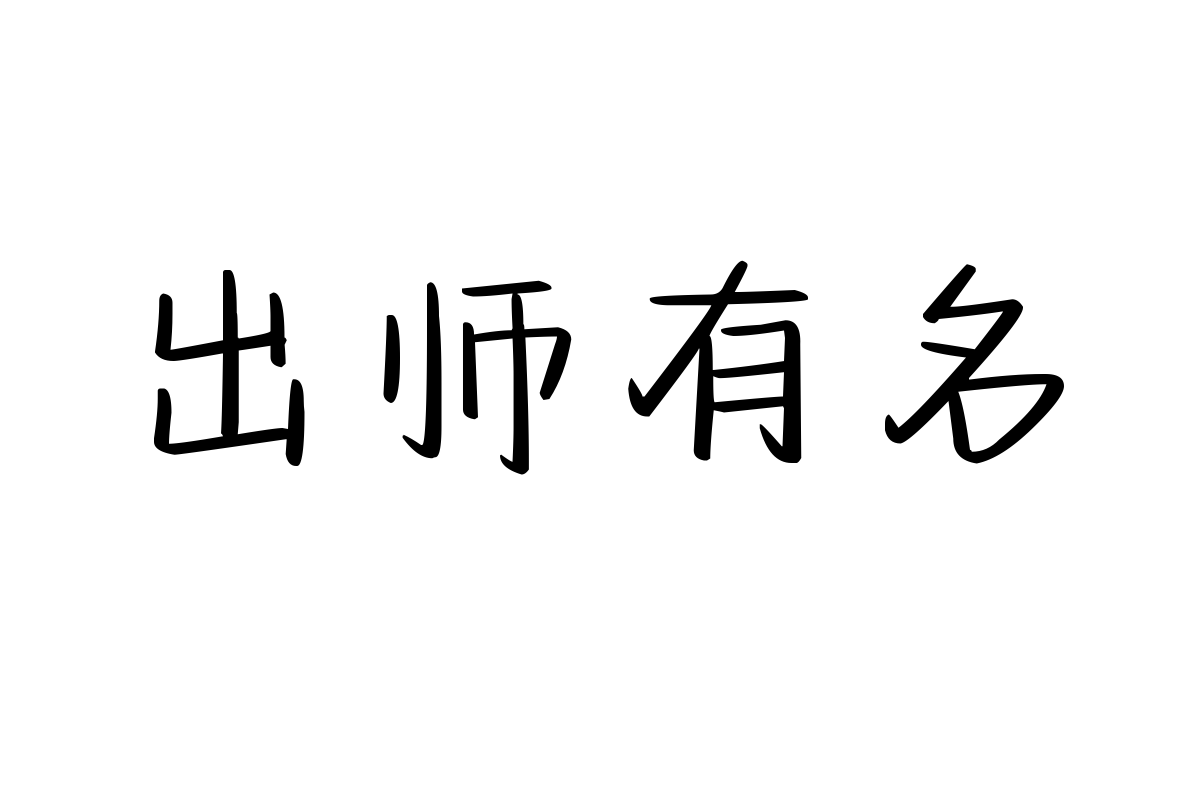
也字工厂综艺弹幕体是一种字体,主要用于综艺节目弹幕中。这种字体的特点是笔画粗细变化明显,给人一种活泼、灵动的感觉。在设计上也注重了与综艺节目弹幕的互动性,使得字体更加符合综艺节目的氛围。
也字工厂综艺弹幕体的特点如下:
1. 笔画粗细变化明显,增加了字体的趣味性和动态感。
2. 笔画连接处有明显的弧度,使得字体看起来更加自然流畅。
3. 字体结构紧凑,易于识别,适合用于弹幕显示。
4. 颜色鲜艳,能够吸引观众的注意力,增加节目的观赏性。
总的来说,也字工厂综艺弹幕体是一种适合综艺节目弹幕使用的字体,它能够为节目增添更多的活力和趣味。
也字工厂综艺弹幕体